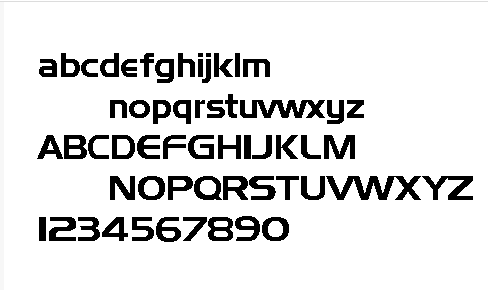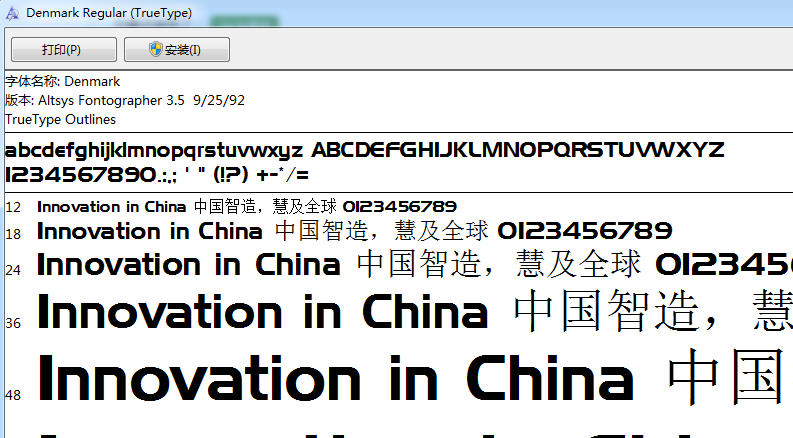
denmark免費(fèi)版適用性非常強(qiáng)的電腦字體,這個(gè)字體一眼看上去就很美觀,視覺(jué)體驗(yàn)很不錯(cuò),并且自帶加粗效果,在設(shè)計(jì)一些英文宣傳報(bào)、封面設(shè)計(jì)時(shí)都可以使用,能夠呈現(xiàn)出很顯眼的效果,其兼容性也很強(qiáng),適用于多個(gè)不同的電腦系統(tǒng)。
denmark是非常漂亮的英文字體,深受廣大設(shè)計(jì)師喜愛(ài),字體被廣泛用于廣告、海報(bào)、畫(huà)冊(cè)、包裝的設(shè)計(jì)及印刷中。
字體設(shè)計(jì)優(yōu)美、秀麗大方,書(shū)寫(xiě)流暢,整體效果非常漂亮。
適合應(yīng)用于海報(bào)設(shè)計(jì)、書(shū)籍裝幀、畫(huà)冊(cè)封面、產(chǎn)品包裝設(shè)計(jì)等應(yīng)用。